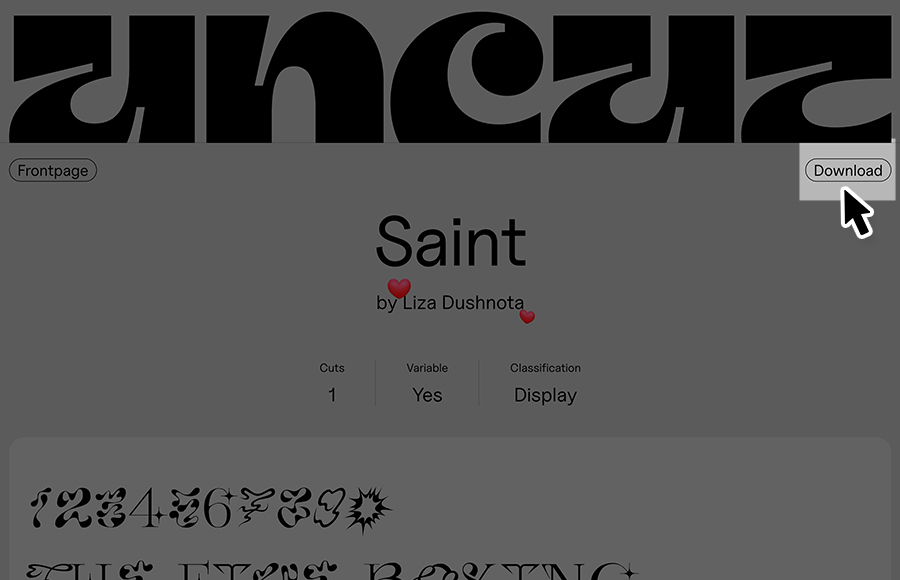
Saintフォントは、セリフ体をベースにしながら、文字の一部に有機的な装飾を組み込んだ遊び心満載なデザインフォントです。
端正な骨格の中に、うねりや曲線や星などのモチーフが入り込み、アート作品のような存在感を放っています。
高級感や神秘性を感じさせるため、ブランドロゴやラグジュアリー系のビジュアル、アートイベントのタイトルなどに適したフォントです。印象に残るタイポグラフィをつくれるフォントです。